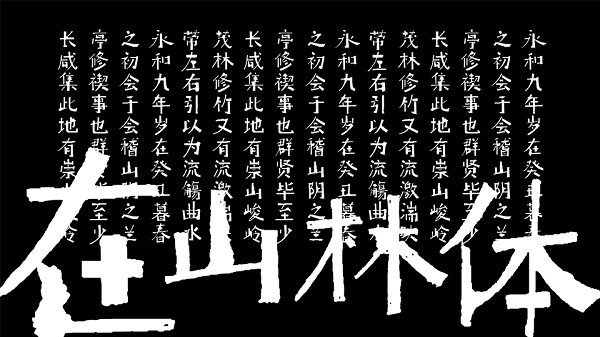
在山林體是喜鵲造字設(shè)計(jì)師推出的一款春之慢野、山林寂靜的鄉(xiāng)村田園風(fēng)字體,給人枝蔓橫生、春意盎然的視覺(jué)體驗(yàn),讓人滿(mǎn)心歡喜,更多有趣字體盡在綠色資源網(wǎng)等你欣賞哦!
適用于小玩趣味又適用于大氣粗曠的標(biāo)題文字,
如書(shū)籍文字、影視標(biāo)題、天然食品、酒菜茶等。